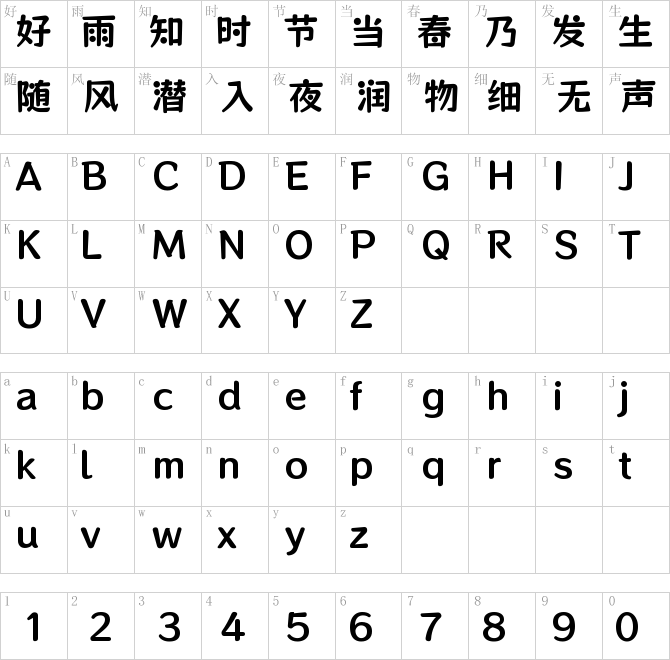
在2023年初,猫啃网携手标小智用心打造了一款卡通字体【标小智龙珠体】,字体风格动感活泼俏皮可爱,非常适合用在卡通类logo设计中,广受大家的喜爱。
后来发现把龙珠体的笔划调整成圆润的风格,看上去效果也非常可爱,别有一番风味,十分适用于儿童,母婴产品以及萌系动画等场合,为此类场景增添天真可爱,无拘无束,自由自在的活力。这款字体除了用作标题,用于正文字体也有一种萌萌的感觉。
于是@Little White Dog对字体整体进行笔划弧度的调整,@频凡兄对字体进行细节上的调整,主要调整转折上部,而比较窄小部分则保持原有的转角,使字体效果看上去更和谐。最后把字体命名为猫啃珠圆体分享给大家使用,请大家尽情享用吧!